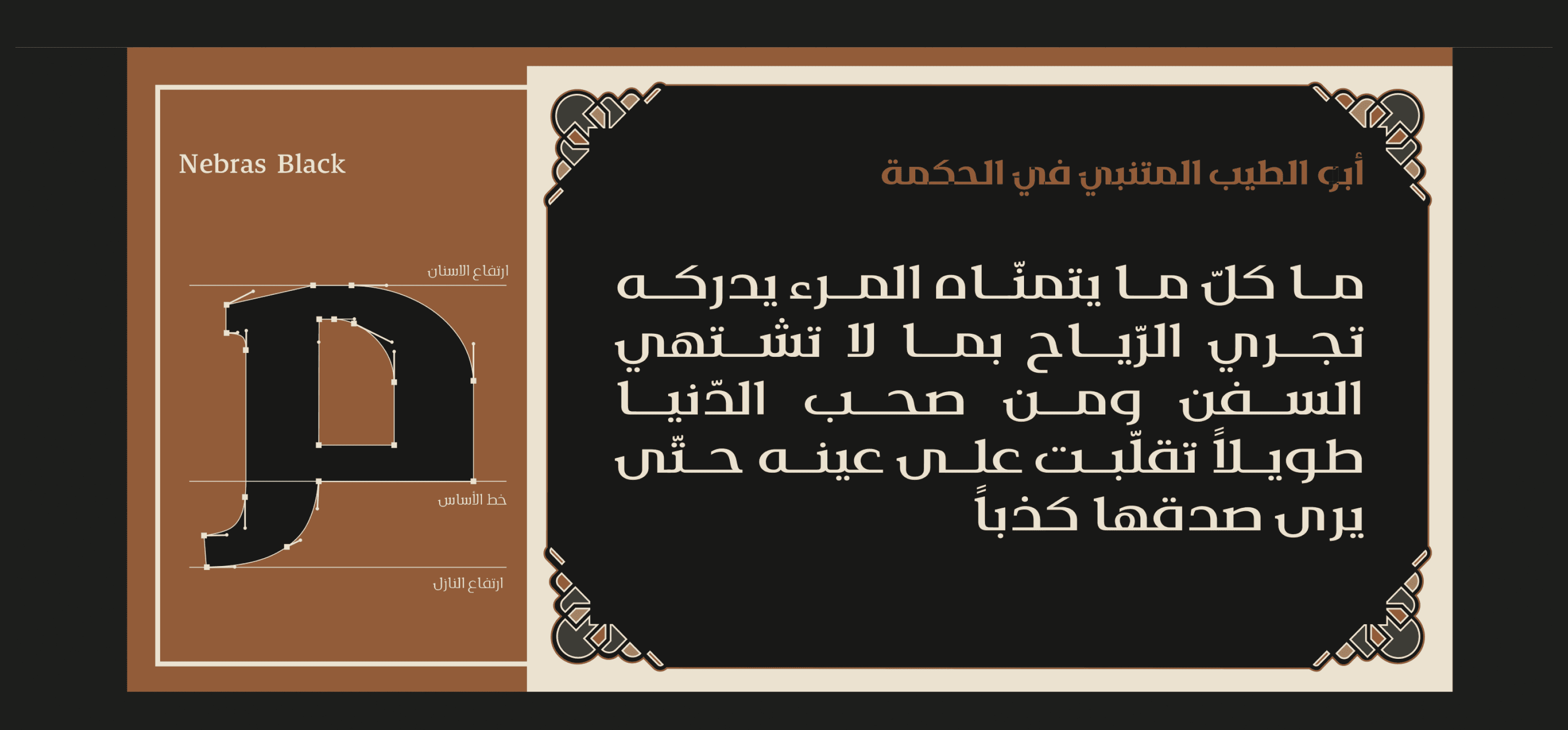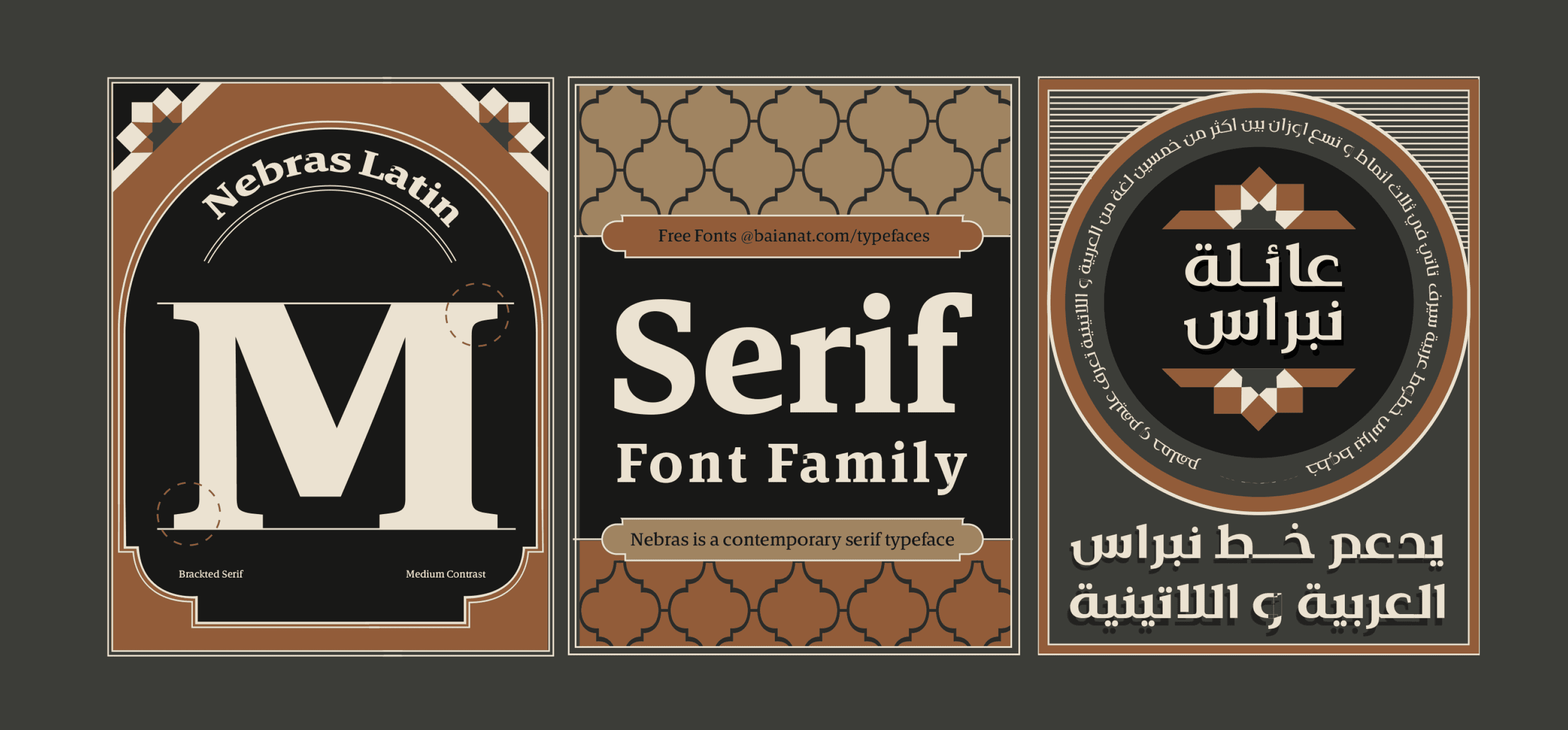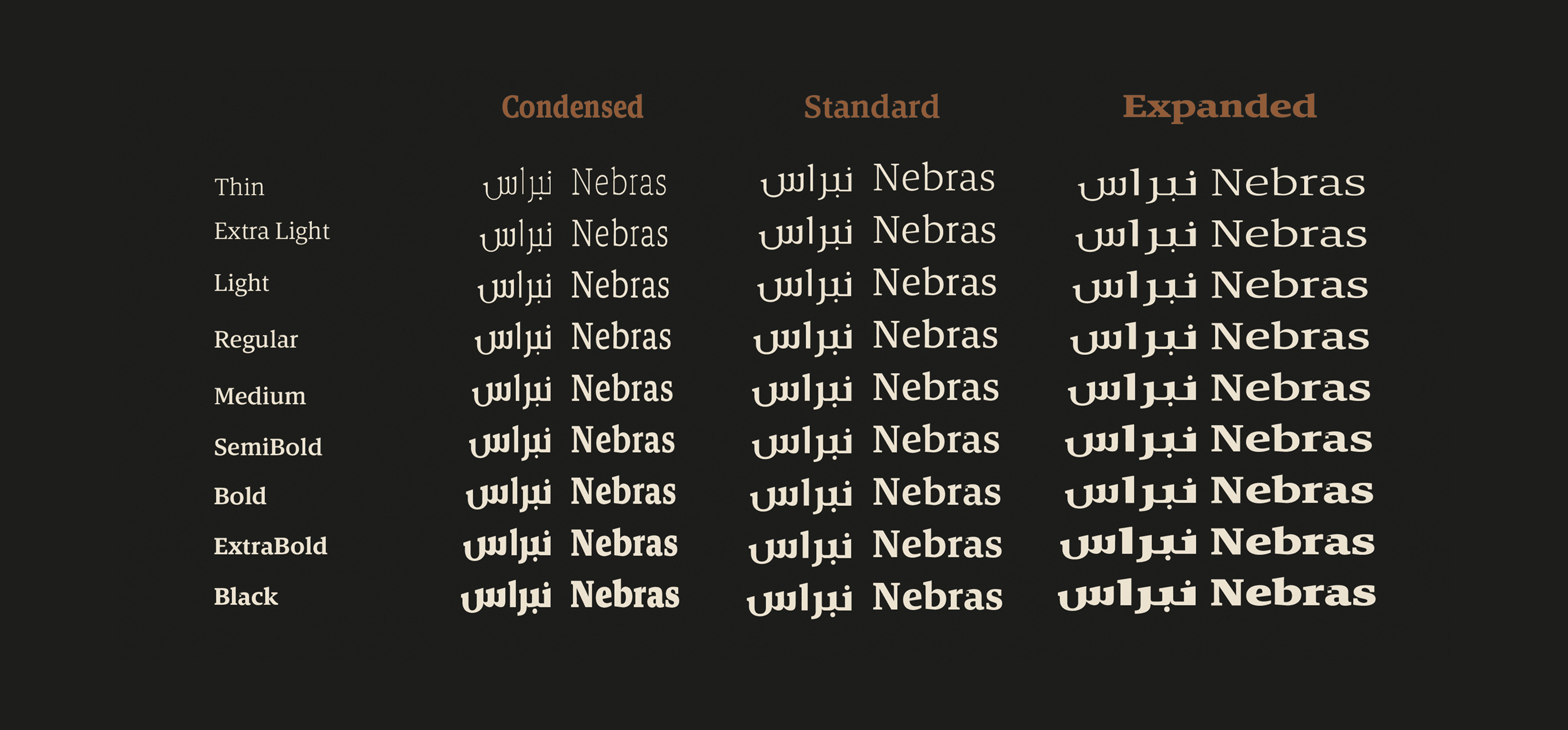
نِبراس هو خط سيريف عصري يتميز بانحناءاته واستدارته، ولكنه أيضًا مستقيم وحاد في بدائله. يتوفر بثلاثة عروض مختلفة وتسعة أوزان، ويدعم أكثر من 50 لغة، تتراوح أنماطه من التصاميم المضغوطة الاقتصادية وسهلة القراءة، إلى الأوزان العريضة والفخمة.